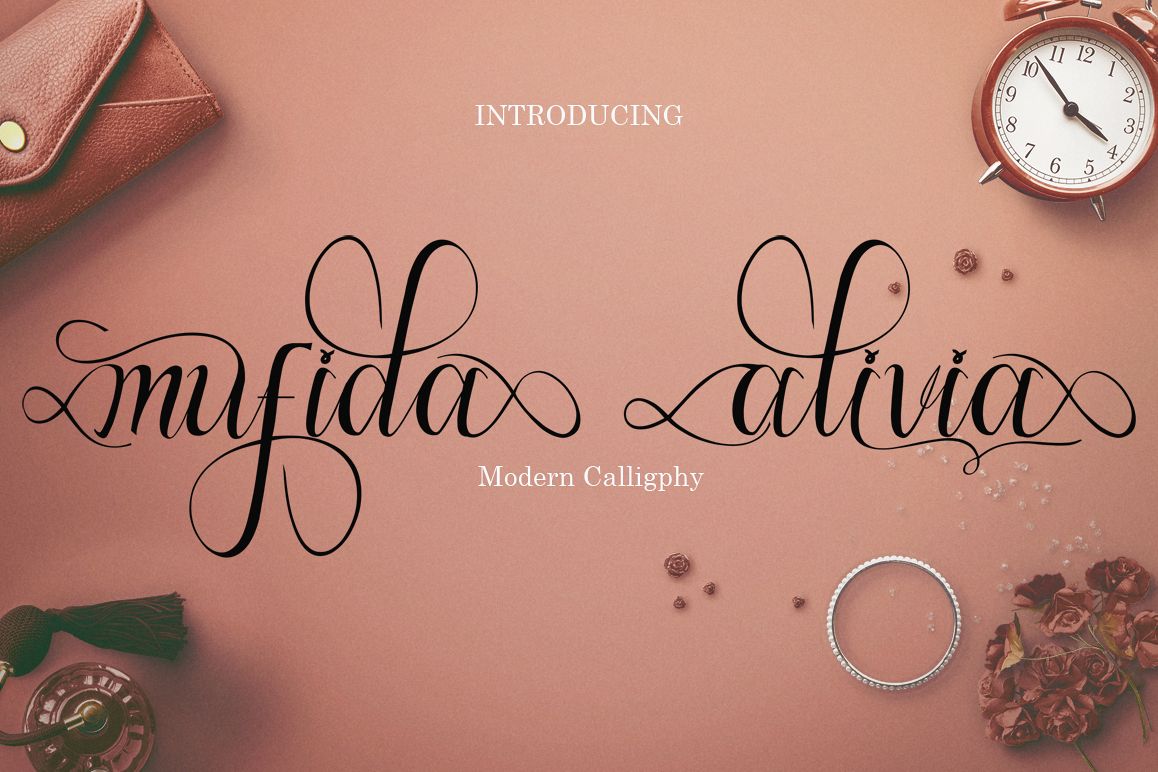
mufida alivia
mufida alivia Script, Hand Lettering Calligraphy Font dengan ombak yang indah dan aliran alami. memiliki gaya huruf yang unik, dengan sentuhan tangan alami, dan memiliki karakter yang lebih lembut dan halus secara halus menghubungkan semua karakter. Mereka memiliki sapuan elegan sederhana dalam huruf terpisah, Anda dapat menggunakan perangkat lunak desain grafis untuk mengakses huruf alternatif.
mufida alivia Script sangat cocok untuk pernikahan, undangan, kartu ucapan, kutipan, poster, branding, kartu nama, stasioner, desain judul, blog header, kutipan seni, seni tipografi, sampul surat buku modern atau desain, gaya yang terjadi seperti desain digambar tangan, judul, surat perkawinan, desain vintage pop, atau tujuan untuk membuat proyek / desain seni kita terlihat cantik dan trendi.
Script mufida alivia lengkap dengan 299 mesin terbang. Ini termasuk huruf besar, huruf kecil, angka, pecahan, tanda baca, dukungan multi bahasa. dan beberapa mesin terbang lainnya adalah variasi yang merupakan bagian dari fitur Open Type seperti, ligatures Standar, set gaya, gaya alternatif. File utama